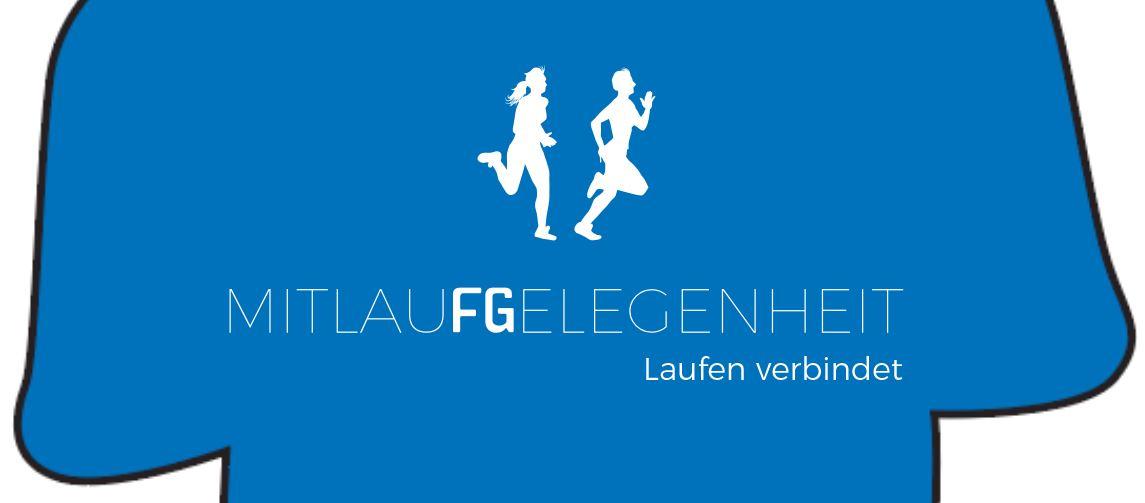
So, mal ein kurzer Zwischenbericht :-) Der Aufwand hat sich gelohnt und wir sind bei fast 200 angemeldeten Startern aktuell (der Lauf ist am Freitag und geplant waren so um die 60 bis 70)  Flyer, Plakat, etc. sind überall zu sehen
Jetzt aber gleich auch wieder eine Bitte in die Runde. Wir wollen aus Refugee-Lauftreff Freiberg jetzt "Miflaufgelegenheit" mit dem Zusatz "Laufen verbindet" machen.  Das fg in Mitlaufgelegenheit soll dabei hervorgehoben werden (ist unser Kfz-Kennzeichen hier und steht für Freiberg).
Logo ist noch in Arbeit aber den Schriftzug würden wir so gern noch auf T-Shirts drucken lassen. Dann hätten alle Helfer am Freitag ein aktuelles T-Shirt mit Silhouette und dem Schriftzug. Habt ihr da eine Empfehlung für die Schriftauswahl?
Meine erste Idee war, das FG in der FE-Schrift, also so wie auf dem Nummernschild?
oder sogar als "abgeschnittenes Nummernschild"  aus dem hier: http://www.peter-wiegel.de/GL_Nummernschild.html
gute Idee und damit würde das FG super auffallen. Dazu eine ganz feine Schrift für den Rest?
Ich mache mich heute Abend mal an einen Entwurf ... Druckerei haben wir gefunden und die helfen uns kurzfristig und zu einem fairen Preis
Eine Nummernschildschrift fänd' ich ja zu holzhammermäßig :hammer:
Ich würde etwas mehr Understatement besser finden – vielleicht das fg mit einem freien Swash unterstreichen, nur leichte Farbvariationen oder mit einem anderen Schriftschnitt auszeichnen.
Schrift? Avenir :-?
Nein, ernsthaft ... was hast du für die Stationen genommen? Montserrat, oder was? Nimm die doch …
Wäre es eine Mitfahrgelegenheit wäre das deutlich schlüssiger. So finde ich es etwas sehr konstruiert. Aber vielleicht gibt es ja eine gute Lösung, überzeuge mich :-)
Wenn es denn trotzdem hervorgehoben sein muss, und sehr schnell wenn ihr wie du sagst noch bis Freitag die Shirts drucken wollt, würde ich jetzt eine schnelle und einfache Lösung suchen. Wenn du das FG unbedingt hervorheben willst müsste ja schonmal alles in Versal gesetzt sein. MITLAUFGELEGENHEIT (in dem Fall ja eine MIDLAUFGELEGENHEIT 8-)).
Einfach das FG in einer anderen Farbe. Schriften hast du doch auf deinem Plakat verwendet, falls ihr Folie druckt etwas serifenloses das sich einfach und schnell entgittern lässt, für das Plakat hattest du was benutzt, die Roboto?. Falls eine zweite Farbe zu aufwändig/teuer ist ein anderer Schriftschnitt, eventuell Outline falls verfügbar? Achte darauf das der Schriftzug nicht zu eng gesetzt ist.
Oder gestalte mit den Farben der Shirts. Sucht eine schöne Farbe aus, blau, gelb, was sich auch in Plakat und Flyer wiederfindet und bedruckt die Shirts weiß, sieht eigentlich immer gut aus. Vielleicht noch eine Verbindung herstellen. Oder die zweite Zeile «Laufen verbindet» auf den Rücken.
Quick and dirty ohne FG hervorgehoben.
Vielen Dank für die Mühe! Ich setzte mich morgen früh man an den Entwurf und bis 11 Uhr muss es dann in der Druckerei sein. Sieht aber so schon echt gut aus.
Ich würde auf dem T-Shirt über dem Schriftzug vielleicht noch die beiden Läufer von dem Banner platzieren, damit es nicht zu "langweilig" wirkt:-?.
Edit: Habe ich in meinem Entwurf schon geändert :-D.
Google: * verbindet
Sprache verbindet
Technik verbindet
Kino verbindet
Yoga verbindet
Elektromobilität verbindet
Kultur verbindet
Erfolg verbindet
Natur verbindet
Leidenschaft verbindet
Die Liste ließe sich endlos fortsetzen. Dass auch Laufen verbindet oder verbinden kann, ist nicht erwähnenswert.
Edit: »Mitlaufgelegenheit« ist weniger eindeutig als z. B. »Offene Laufgruppe«.  »Laufen verbindet« befriedigt nur den Erklärungsbedarf. Ich erinnere mich, dass du hier schon einmal nach einer passenden Bezeichnung für eure offene Laufgemeinschaft gesucht hast.
Ist aber der Slogan der Kampagne/Aktion...
Was für eine Aktion meinst du? Ist das eine bundesweite oder städteübergreifende Kampagne? Und falls ja: Muss er deshalb aufgegriffen werden?
... und dafür sind Slogans auch gemacht! Eben dass sie einprägsam und manchmal eben auch
sind.:nicken:
Wir sind, das ist hier inzwischen bekannt, für jede Kritik offen. Ob der "laufen verbindet" überhaupt sein muss, ist ja auch eine der Fragen. Als Bezeichung die "Mitlaufgelegenheit" mit dem FG als Bezug zu Freiberg kann auch allein stehen.
Für die Laufgruppe wird es ein neues Logo geben und in dem Zusammenhang auch endlich T-Shirts für alle in der Gruppe. In dem Zusammenhang ist die Entscheidung dann wichtig.
Jetzt "nur" das T-Shirt für den Lauf und dazu morgen früh der Entwurf.